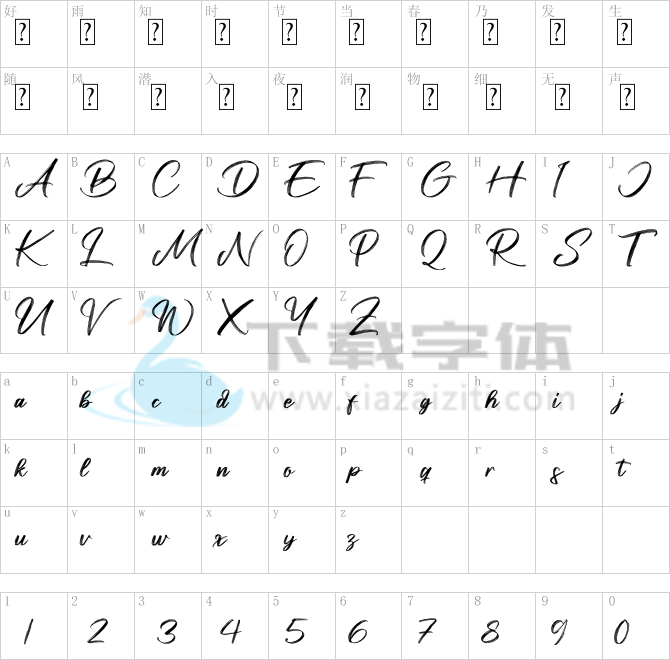
Amsterdam Laviera.otf字体下载,这款字体结构工整、笔画清晰,兼顾美观与易读性,适用于标题、正文、海报、包装、LOGO 等多种场景。字形优雅稳定,风格百搭耐看,适配日常排版与创意设计,让文字呈现更舒适、更具质感。Amsterdam Laviera.otf字体下载一笔一画,皆是细节,以均衡的比例、流畅的线条打造舒适视觉体验,字形端正大气,风格简约现代。无论是商业设计、品牌宣传还是日常排版,都能轻松驾驭,让文字更有格调与力量。Amsterdam Laviera.otf字体下载字体下载。
• 字体名称:Amsterdam Laviera